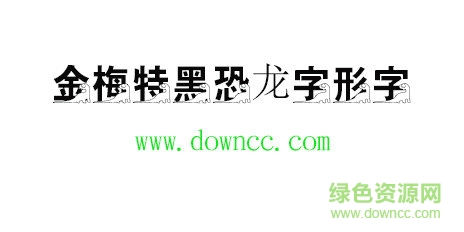
金梅特黑恐龍字形字體是一款非常好看的金梅繁體字體,支持中文、英文和阿拉伯數(shù)字的輸入,當輸入中文的時候,右下角會出現(xiàn)一個白色的恐龍樣式的圖案,非常的炫酷,喜愛的朋友趕快到綠色資源網(wǎng)下載體驗吧!
1.筆畫端正均勻,筆形清秀、舒展,結構寬博。
2.橫豎筆畫粗細差別不明顯,可作為雜志和書籍的正文首選字體。